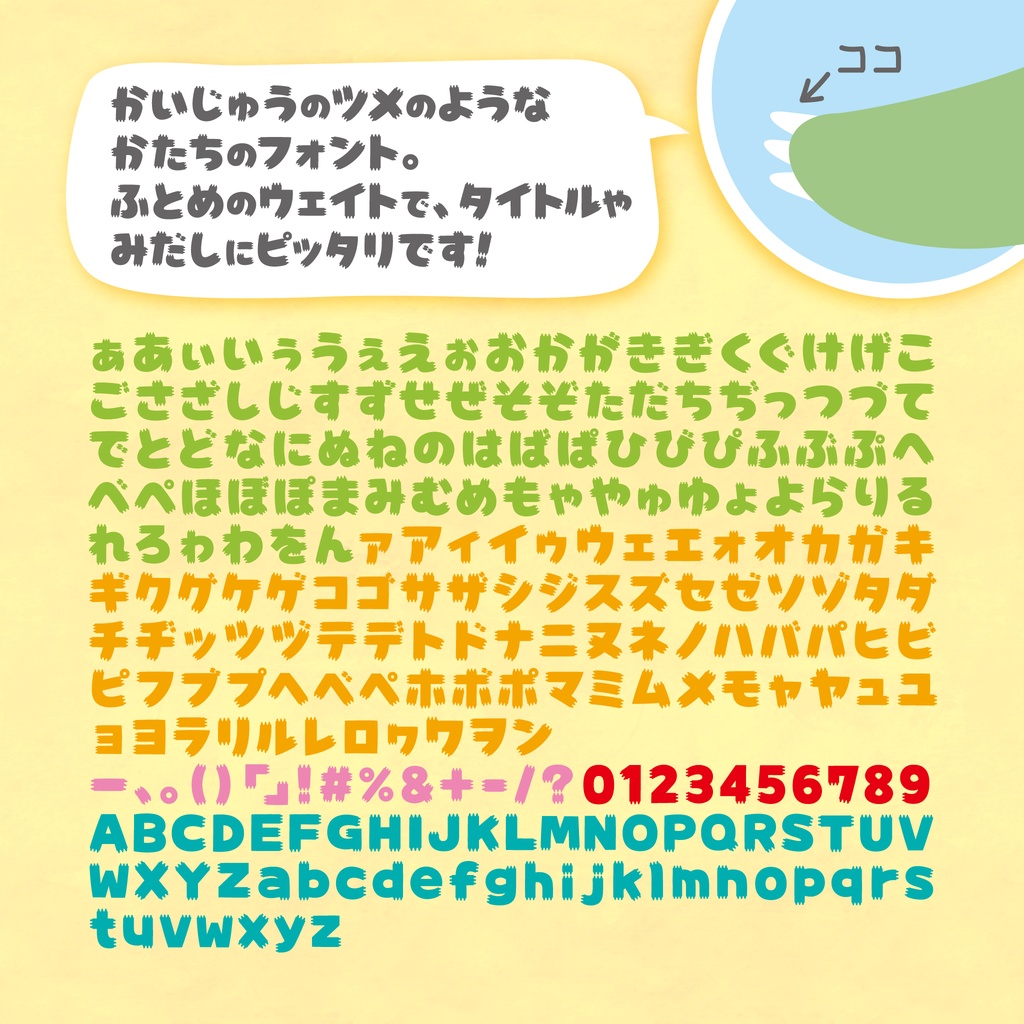
かいじゅうフォント
※無料版はカタカナと一部記号のみとなります。 「かいじゅうフォント」は、怪獣のツメのようなエレメントが特徴的なデザインフォント。太めのウェイトでタイトルや見出しに最適です。 【通常版】収録文字 ぁあぃいぅうぇえぉおかがきぎくぐけげこごさざしじすずせぜそぞただちぢっつづてでとどなにぬねのはばぱひびぴふぶぷへべぺほぼぽまみむめもゃやゅゆょよらりるれろゎわをんァアィイゥウェエォオカガキギクグケゲコゴサザシジスズセゼソゾタダチヂッツヅテデトドナニヌネノハバパヒビピフブプヘベペホボポマミムメモャヤュユョヨラリルレロヮワヲンー、。()「」!#%&+-=,./?0123456789ABCDEFGHIJKLMNOPQRSTUVWXYZabcdefghijklmnopqrstuvwxyz フォントデータ形式:OpenType 印刷物・立体制作物・web・ゲーム・映像・電子書籍・LINEスタンプ(絵文字は不可)などにお使いいただけます。 変形・加工も可能です。 ロゴマーク等、商標登録する際は加工した画像のみ商標登録できます。